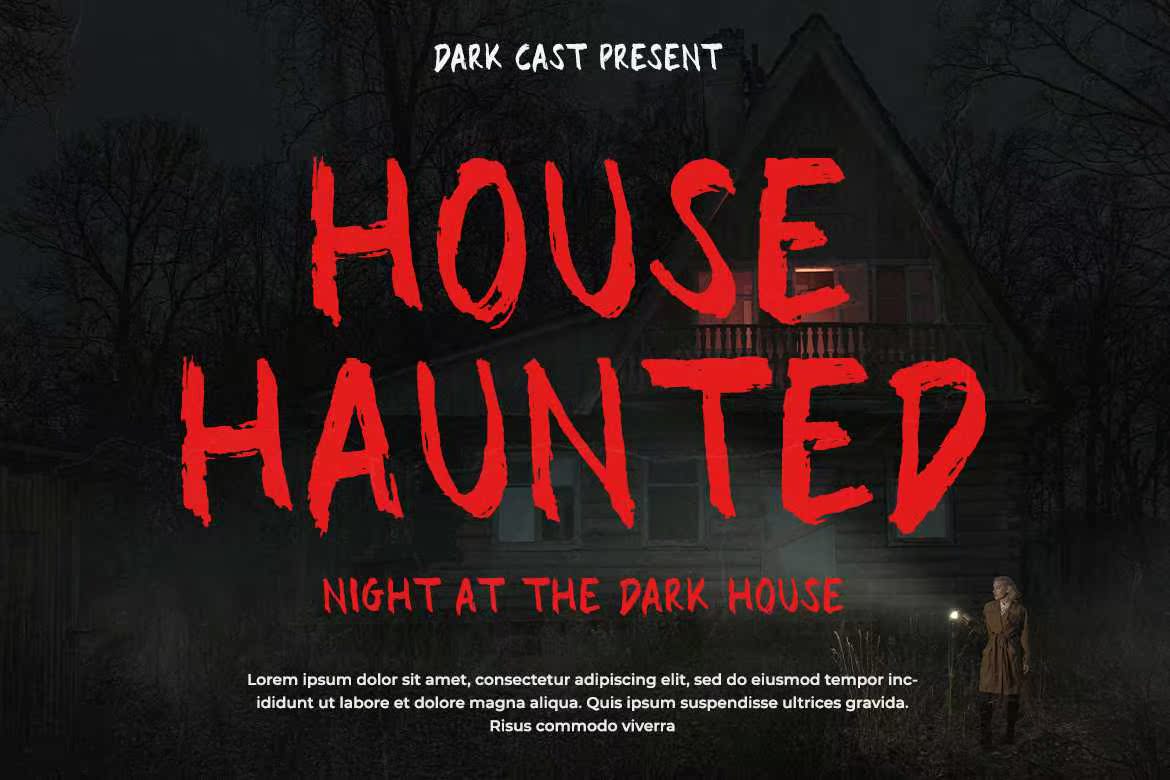
你一直在追求一种“令人不寒而栗”的字体?一种可以为你的作品、客户或其他任何人提供持久的笔触风格的字体?这是一种错误的想法,这种笔触的字体是你一直在追求的所有东西。这并不意味着你正在重新创造游戏恐怖、T恤或是你想要提供给Escary的画作——这种字体将是任何一个具有超恐怖、哥特式风格的项目,刷子,恐惧感和手感。你一直在使用一种“令人不寒而栗”的字体?一种可以为你的作品、客户或其他任何具有刷子风格的人提供永久性快乐的字体?这是错误的,刷子的字体是你一直以来喜欢的所有东西。这并不意味着你在再现游戏恐惧,这件T恤或是手工制作的,它将为所有的项目提供额外的怪异、哥特式、毛刷、恐怖和手感。